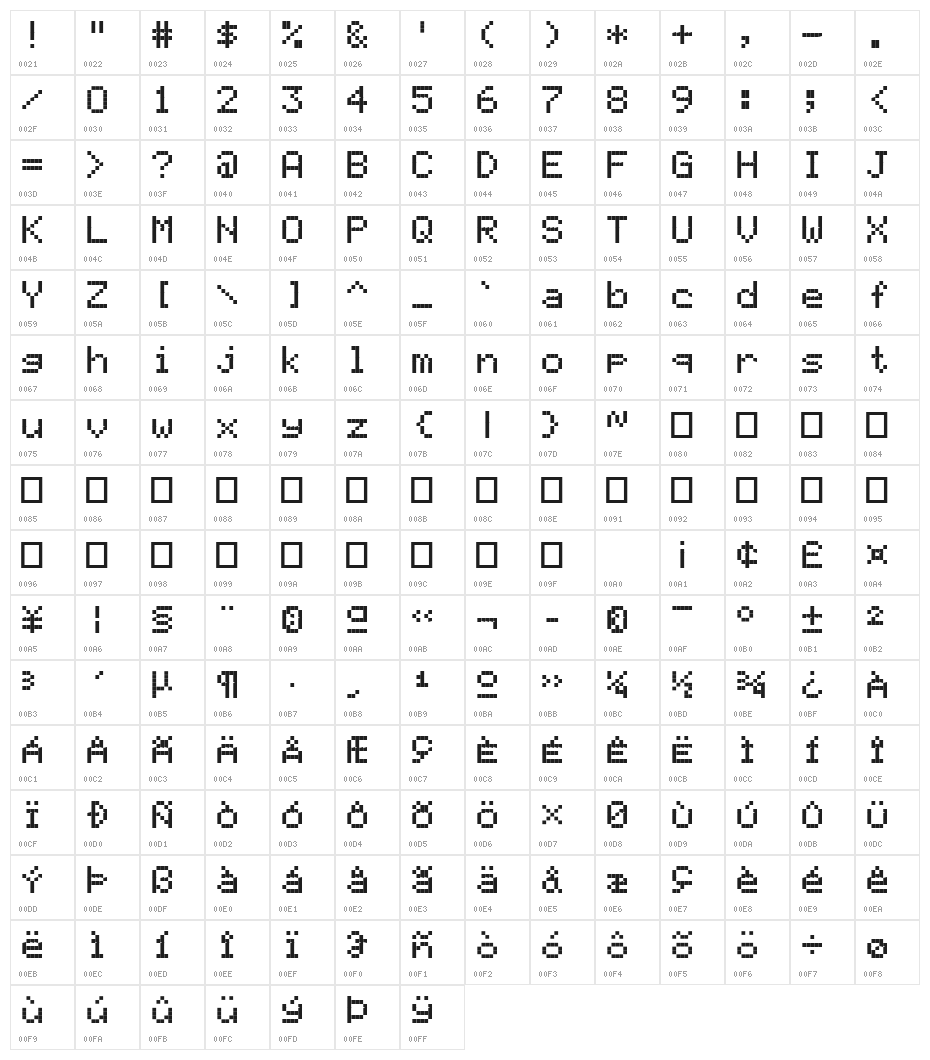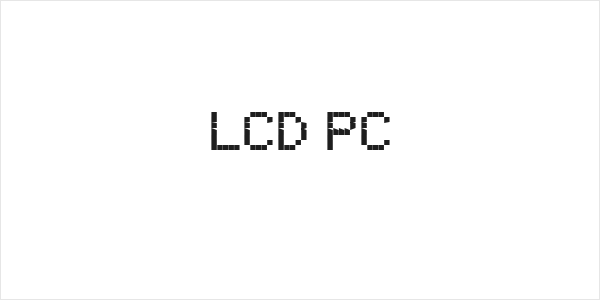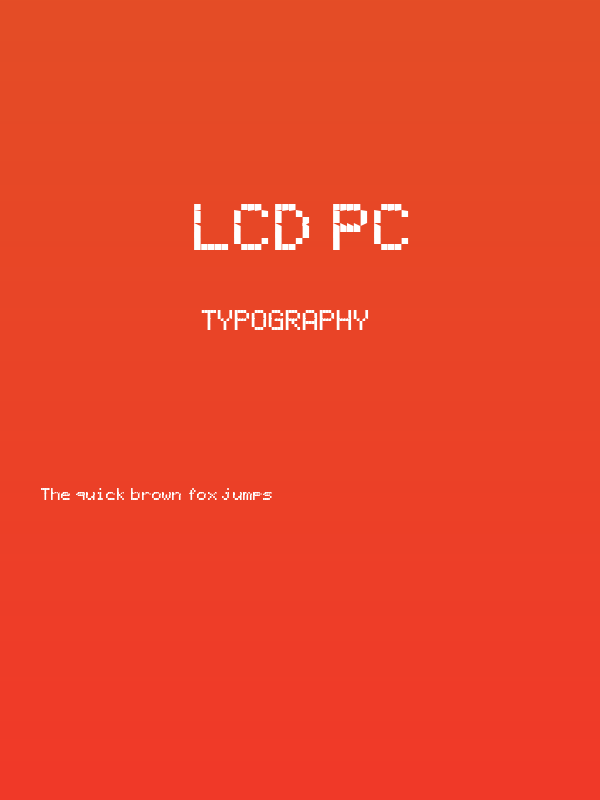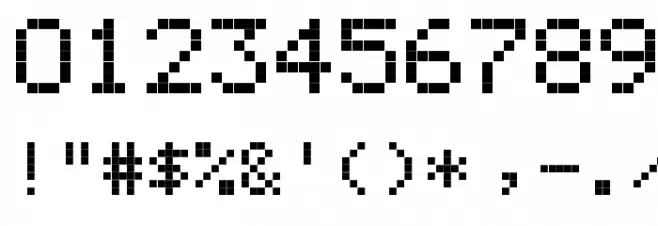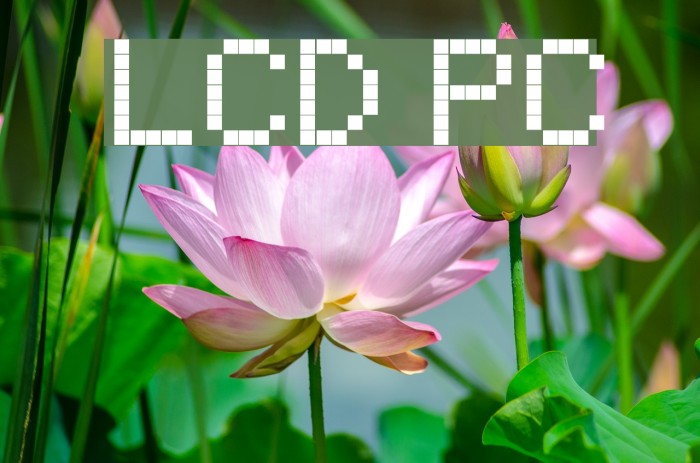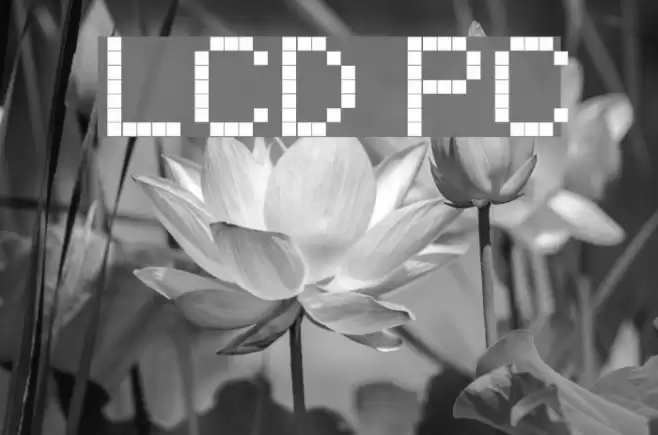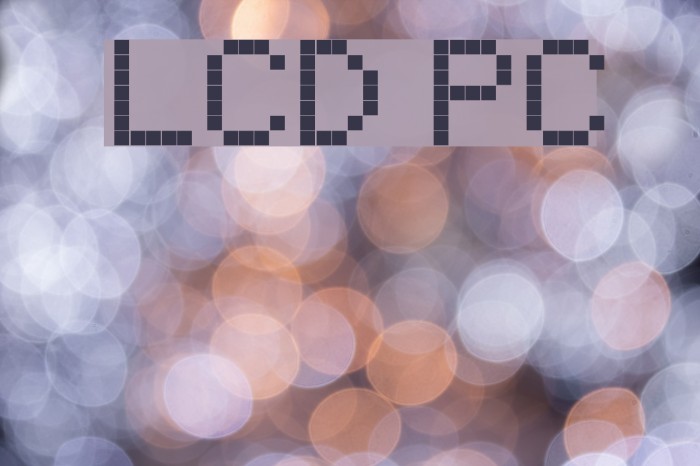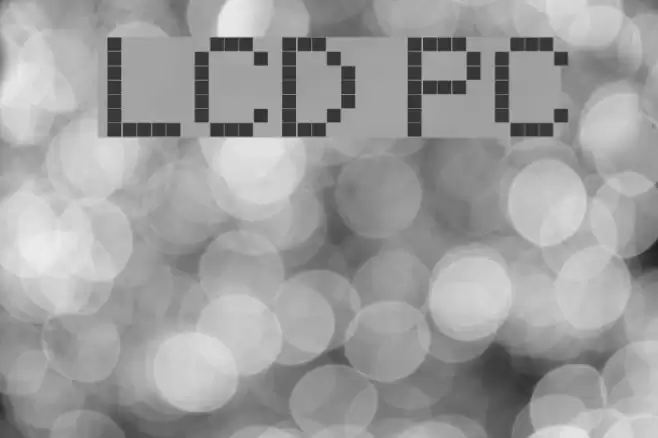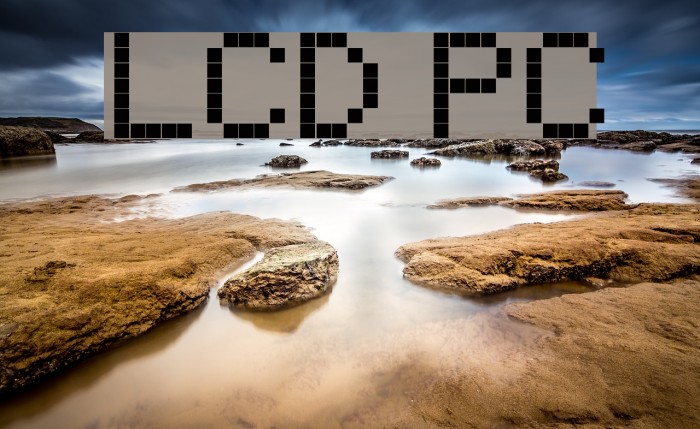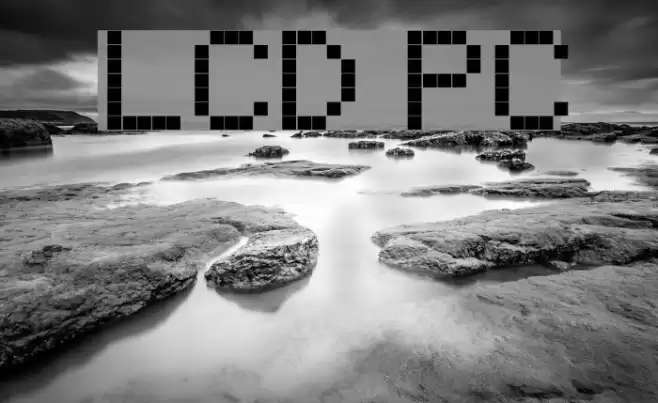
LCD PC Font
| Categorii | Pixel |
| Stil general | Retro, Digital |
| Caz de utilizare | Headlines, Digital displays, Logos |
| Proiecte propuse | Ideal for digital displays, retro-themed designs, video game graphics, and tech-related branding. |